秀英体のコネタ
第8回 活字の宇宙の中の秀英体
『活字の宇宙 Robunndo Type Cosmique』
2005年6月20日(月)~7月下旬 青山ブックセンター 六本木店
青山ブックセンター六本木店で、「活字の宇宙」と題し、文字にまつわる本のフェアが2005年6月20日から7月下旬まで開催されています。なんとそちらに『秀英体研究』も置かせてもらえるということで、初日にさっそくおじゃましてきました。
青山ブックセンター六本木店の入口からまっすぐつきあたりでフェアは開催されています。
かなり広いスペースがフェアに使われています。
まず目に入るのは、中央に設置された透明の大きなケースです。この中には、『秀英体研究』とその箔押しに使った版、写研の秀英明朝SHMのメインプレート、島屋政一『本木昌造伝』(朗文堂)などが展示されています。
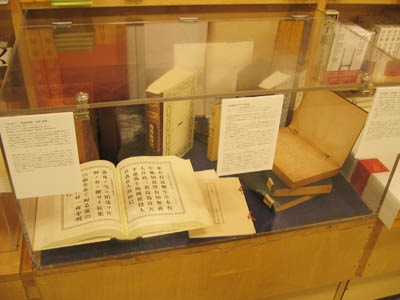
いました!『秀英体研究』です!
ここに飾ってある銅版は、函や表紙にあしらわれた花形装飾活字の版です。『秀英体研究』の巻末にも記載されていますが、この花形活字は明治36年に秀英舎鋳造部製文堂が発行した活字見本帳『活版見本帳 Type Specimens』に掲載されていた第34番をデジタル化したものです。奇しくも『活版見本帳 Type Specimens』の発行から、ちょうど100年が経っていました。
この版は腐食銅板ですがタイトルなど文字の箔押し版は手彫真鍮版です。
ちなみに『秀英体研究』では3色の箔を使用しています。表紙のタイトル・著者名はゴージャスな印象の金26番、表紙の花形活字と背のタイトル・著者名は白の強い上品な金105番、背の花形活字は艶消し金2番を使用しました。
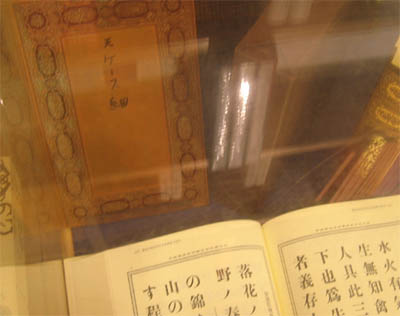
表紙などに使用した版
もちろん展示されているだけでなく、実際に販売して頂いております。『本木昌造伝』、堀辰雄『花あしび』(朗文堂)など、しっかりとした装幀の本のそばに並んでいました。
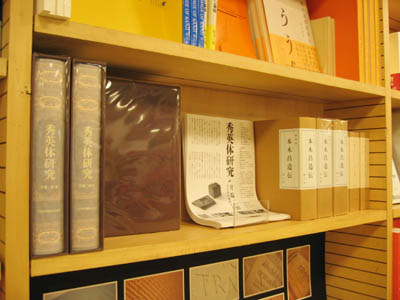
となりには『本木昌造伝』が。夢のコラボ。
参考として展示されていたタイポグラフィTシャツは、フェアのそばの天井に飾られています。
タイポグラフィTシャツコーナー
なんと!秀英体Tシャツもありました。昭和4年に発行した活字見本帳『明朝初号活字見本帳』からひら仮名のページがTシャツになっています。となりは平野富二の平野活版製造所(のちの東京築地活版製造所)のマークです。
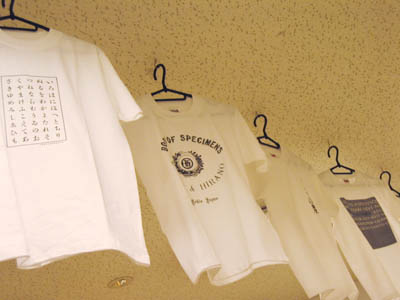
秀英舎Tシャツ(左端)と平野活版Tシャツが仲良く並んでいます。
『字統』『常用字解』『白川静著作集』(いずれも平凡社)など代表的なお仕事が並びます。『別冊太陽 白川静の世界―漢字のものがたり』(表紙に秀英初号が!)もあります。
タイポグラフィに関係する本は、デザイン・日本語・コンピューター・歴史・洋書などバラバラに置いてあり、なかなかまとまっていなかったりします。定番の本から新しい本、話題の本までバラエティに富んだ組み合わせ(そして『秀英体研究』も!)のフェアですので、みなさまぜひ足を運んでみてください。
新潮文庫のYondaちゃんがタイポグラフィTシャツを欲しそうな顔をしています。